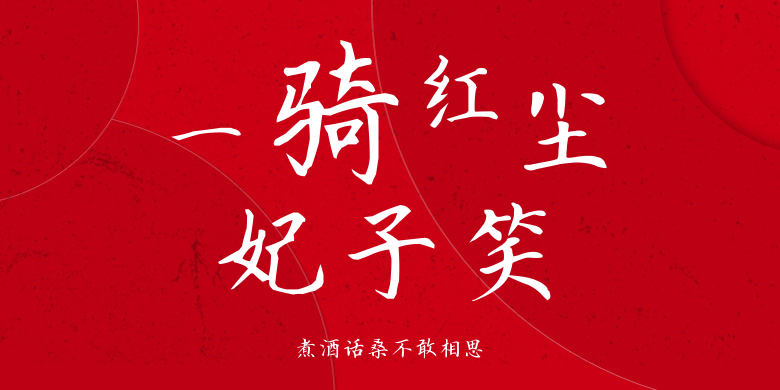
煮酒话桑不敢相思
煮酒话桑不敢相思,这款字体结构工整、笔画清晰,兼顾美观与易读性,适用于标题、正文、海报、包装、LOGO 等多种场景。字形优雅稳定,风格百搭耐看,适配日常排版与创意设计,让文字呈现更舒适、更具质感。煮酒话桑不敢相思一笔一画,皆是细节,以均衡的比例、流畅的线条打造舒适视觉体验,字形端正大气,风格简约现代。无论是商业设计、品牌宣传还是日常排版,都能轻松驾驭,让文字更有格调与力量。煮酒话桑不敢相思字体下载。